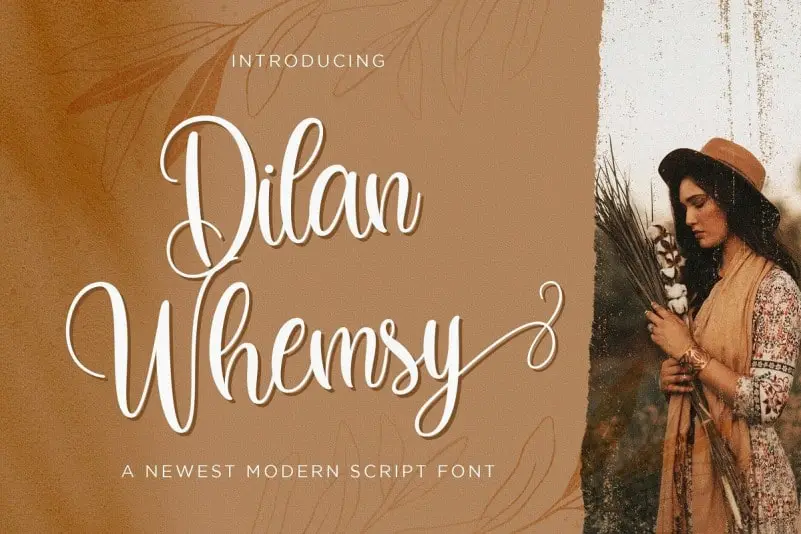
Dilan Whemsy Calligraphy Font – Download Grátis
A fonte “Dilan Whemsy Calligraphy” é uma face tipográfica à mão dura, criada por StringLabs em 99designs. Ela traz a autêntica essência do estilo script, com sua elegância e beleza naturalmente presentes. Este tipo de fonte é perfeitamente adaptável para projetos de design que buscam uma harmonia sofisticada e delicada. Seja um projeto pessoal ou corporativo, “Dilan Whemsy Calligraphy” irá adicionar um toque distintivo e vibrante à sua criação. Suas letras bem equilibradas e elegantes garantem uma integração perfeita em uma ampla variedade de projetos. Adicione-a aos seus ideais mais criativos, observe como ela os transforma e dá vida a eles!